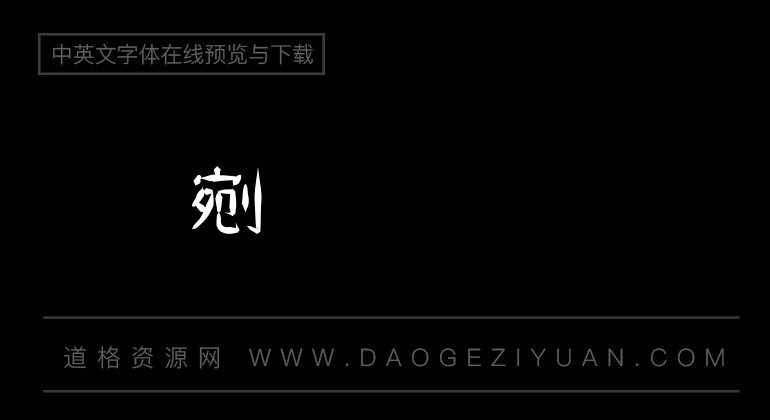
金梅新版塊字範例
金梅新版塊字範例字體是一款簡潔大氣的中文字體,它以經典的楷體為基礎,融入了現代元素,擁有更加清新的線條,更加優雅的視覺效果。字體的筆劃更加細膩,更加精緻,更加符合現代文字設計的審美觀,適合用於各種文字設計,可以為文字提供更加豐富的表現力。
金梅新版塊字範例是一款非常不錯的手寫藝術字體,具有很好的視覺感,適合於文化類的宣傳設計、商業類品牌的廣告和產品包裝設計以及個性化文字排版等較多場景。